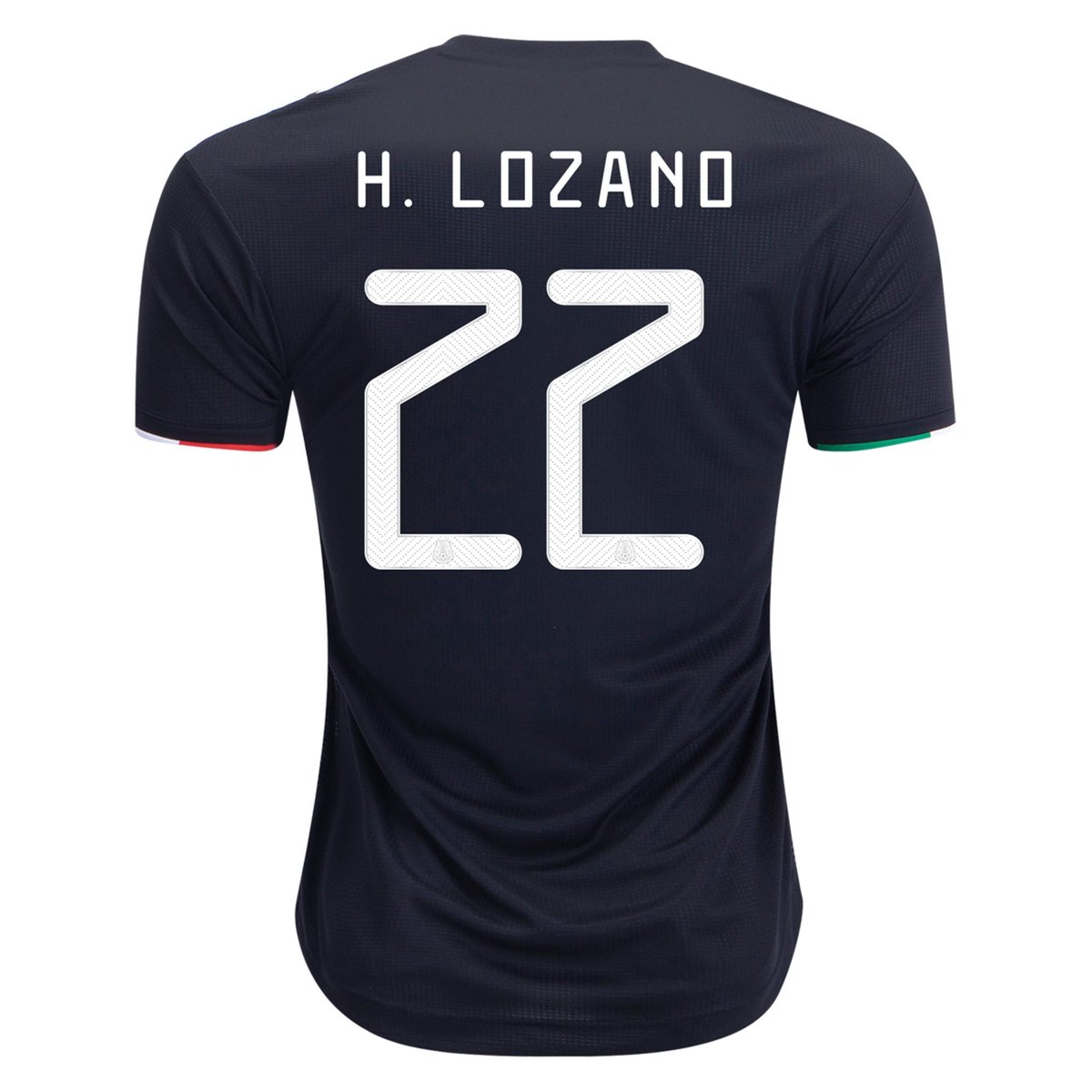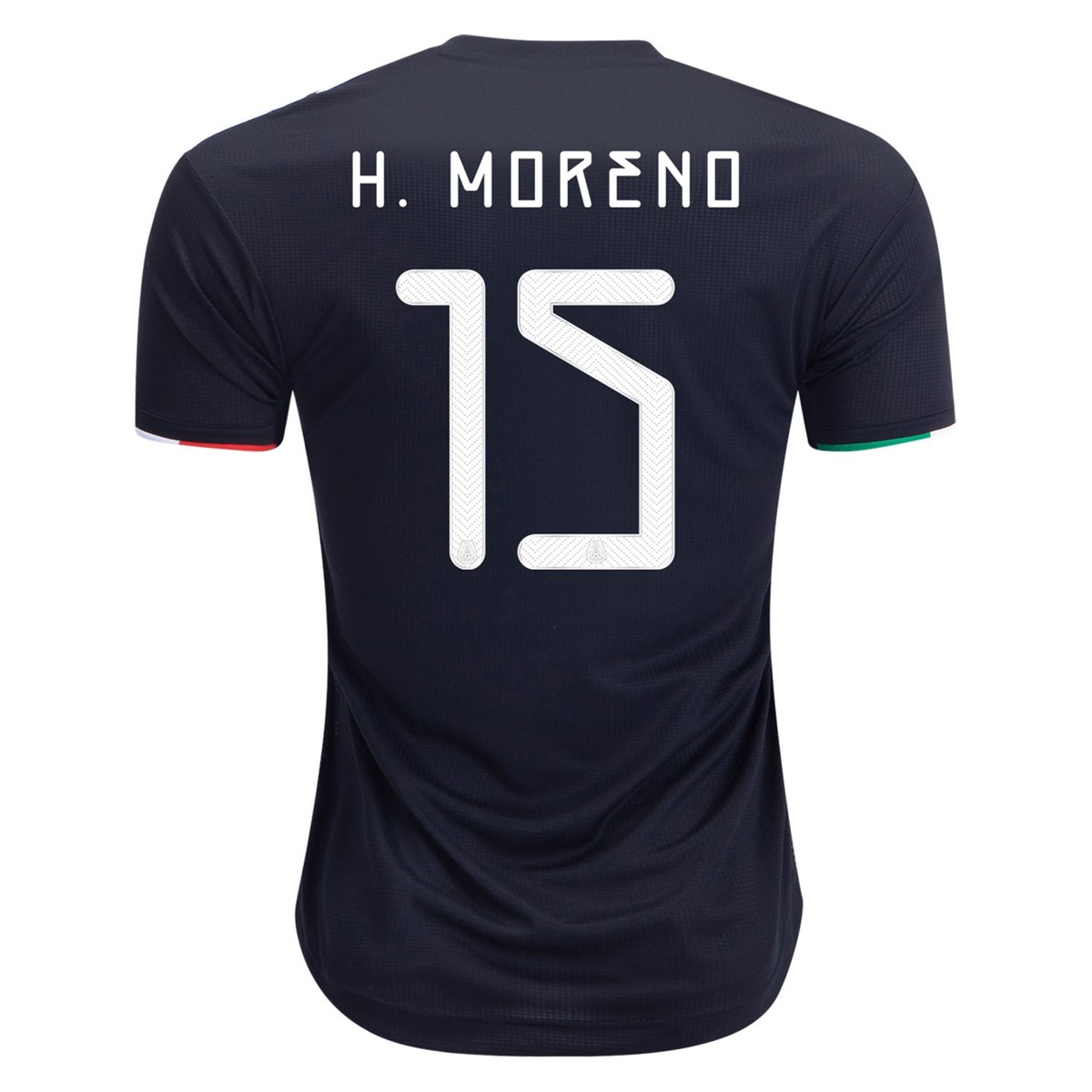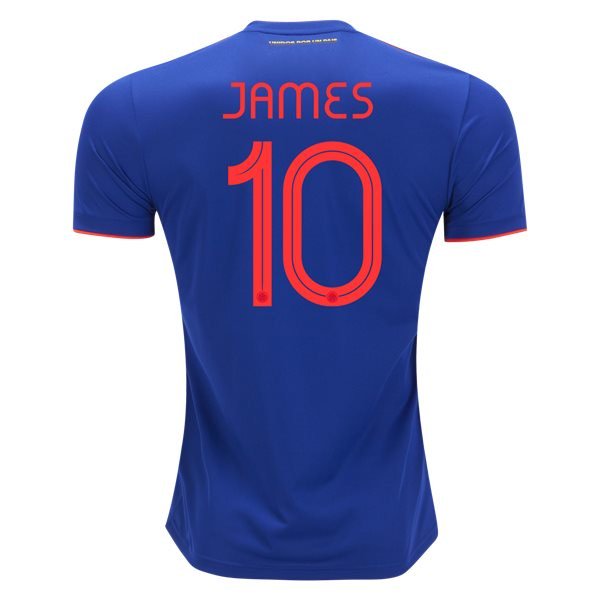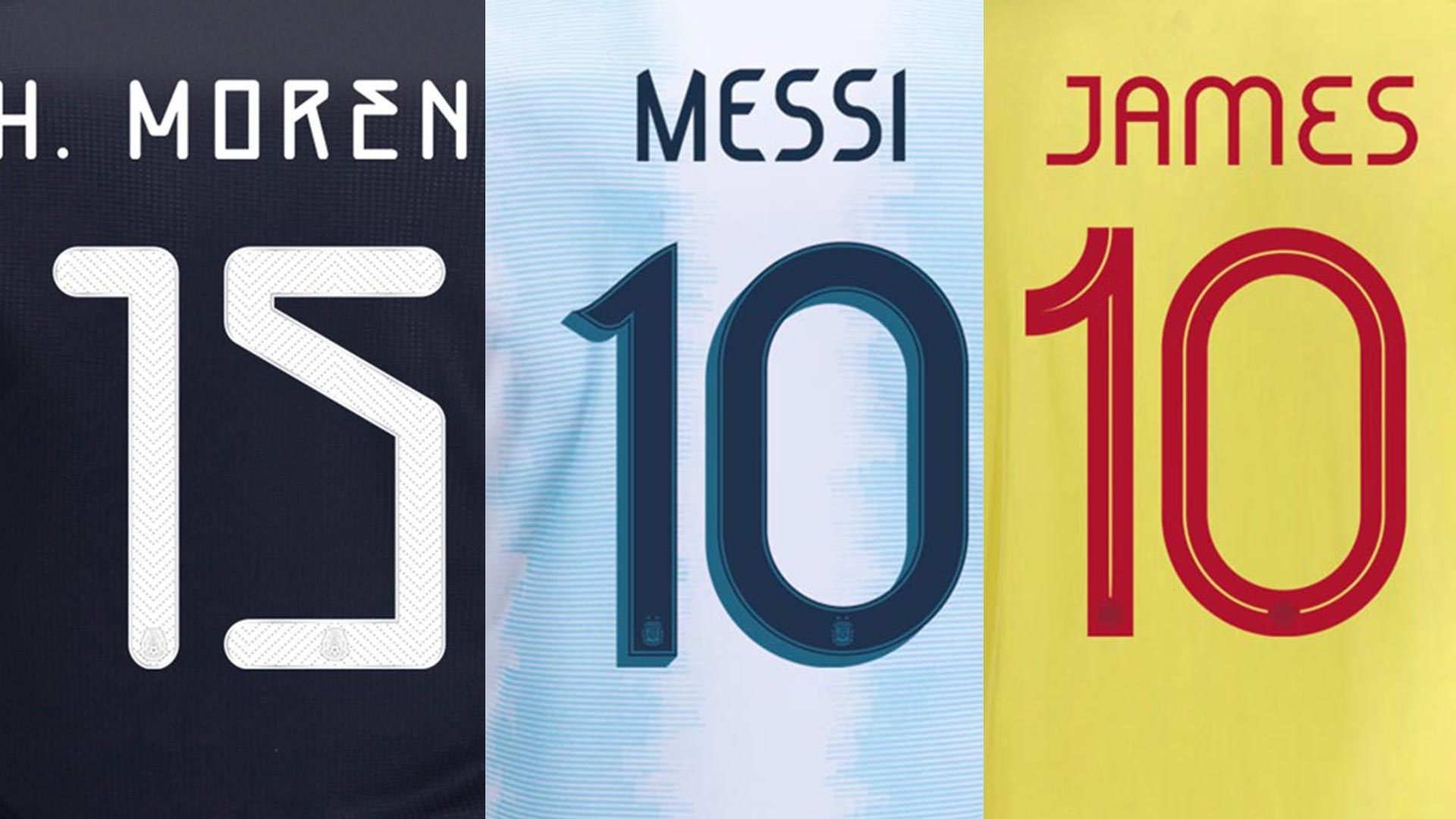
Für jedes Team einzigartig | 3 Adidas 2019 Trikot-Schriftarten für Nationalmannschaften veröffentlicht
Adidas hat gestern ihre neuen Trikots für Copa America 2019 und Gold Cup 2019 vorgestellt, also die Trikots für Argentinien, Kolumbien und Mexiko. Zusammen mit dem Launch erhalten wir endlich einen Blick auf die Schriftart der neuen Adidas 2019 Nationalmannschaft-Trikots.
Anders als früher, als alle Adidas-Teams die exakt gleiche Schriftart erhielten, wird die Schriftart für jede der drei Nationalmannschaften von Adidas maßgeschneidert sein. Neue Trikots haben Argentinien, Kolumbien und Mexiko erhalten.
Adidas 2019 Nationalmannschaft Trikot-Schriftarten
Jede der drei neuen Adidas-Schriftarten wurde exklusiv für jede Nation entwickelt. Interessanterweise beinhalten die Argentinien-Nummern auf der Vorderseite das AFA-Logo.
Argentinien
Die Adidas Argentinien 2019 Schriftart wurde mit Blick auf das AFA-Logo (Argentina Football Association) entworfen. So weist beispielsweise die Nummer 1 der Argentinien-Schriftart eine leichte Kurve auf, die vom AFA-Wappen inspiriert wurde (danke an La Casaca für diese Entdeckung).
Kolumbien
Die Kolumbien 2019 Schriftart zeichnet sich durch einen eleganten Look mit einer schlanken Innenlinie aus.
Mexiko
Die Adidas Mexiko 2019 Schriftart setzt auf einen futuristischen Ansatz, der dem modernen Design des Trikots entspricht.
Die drei Adidas-Teams, die neue Heimtrikots erhalten haben, werden ihr Auswärtstrikot für 2019 übernehmen. Die Nummern und Buchstaben der Argentinien, Kolumbien und Mexiko 2019 Auswärtstrikots werden anstelle der Adidas WM 2018 Schriftart auch die jeweils neue Schriftart aufweisen.